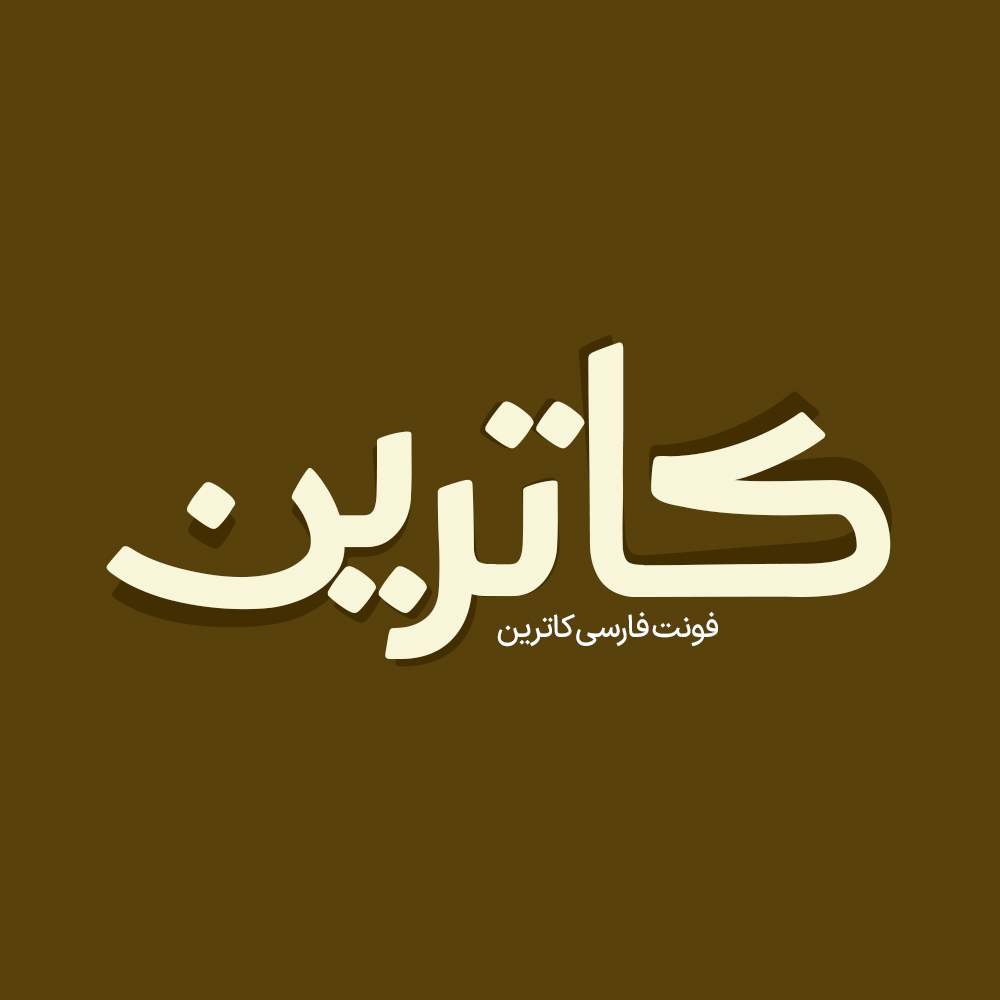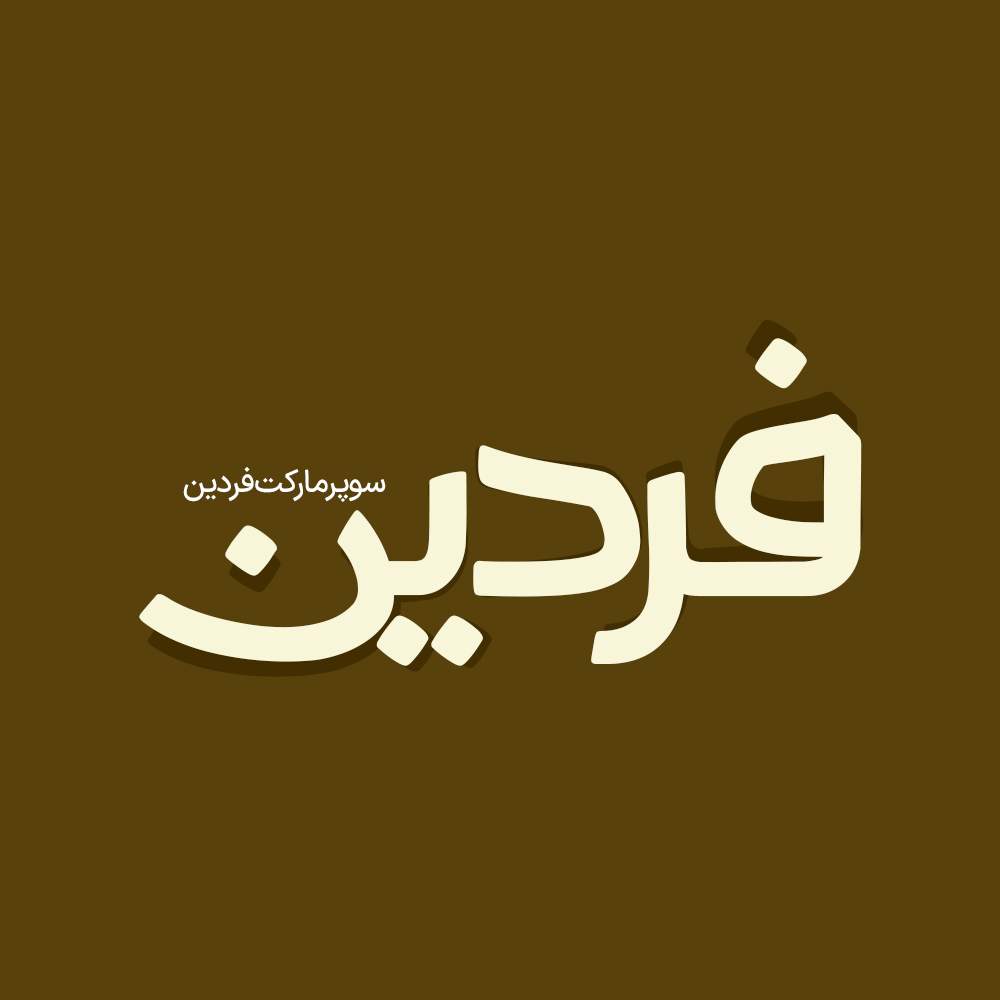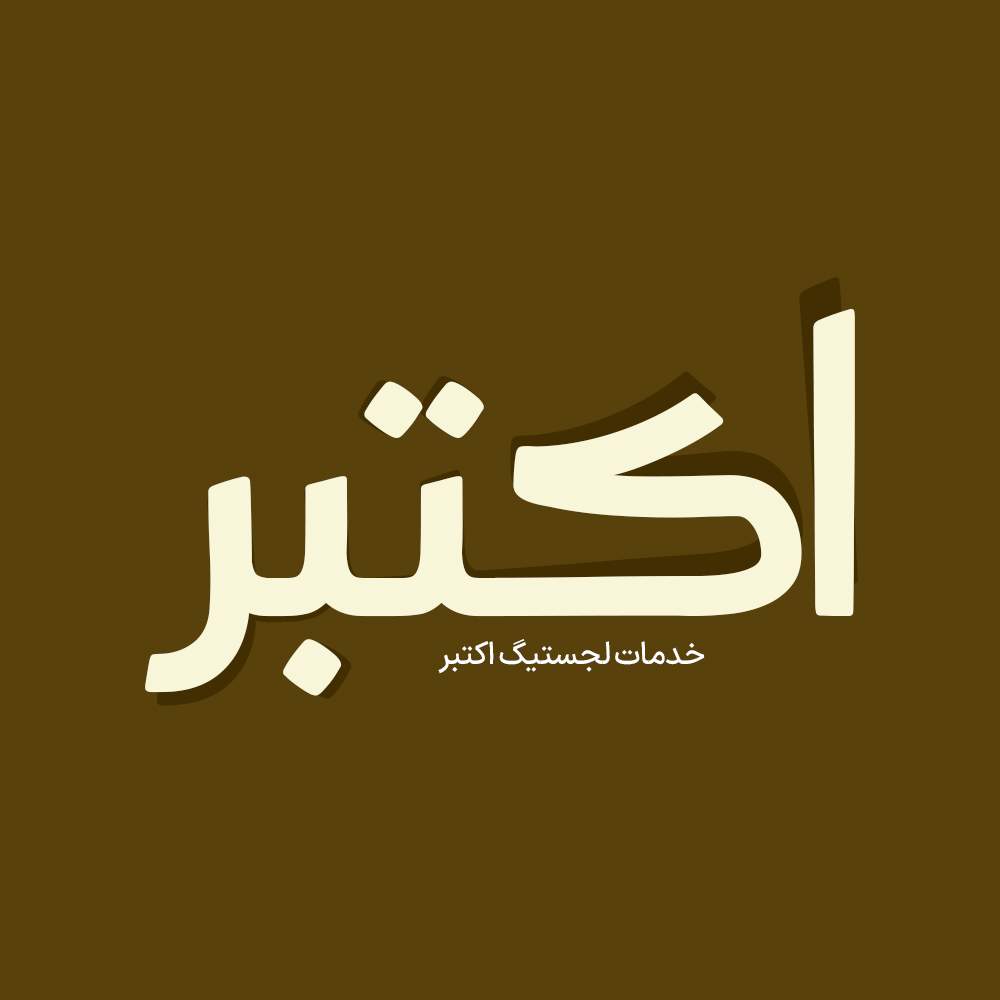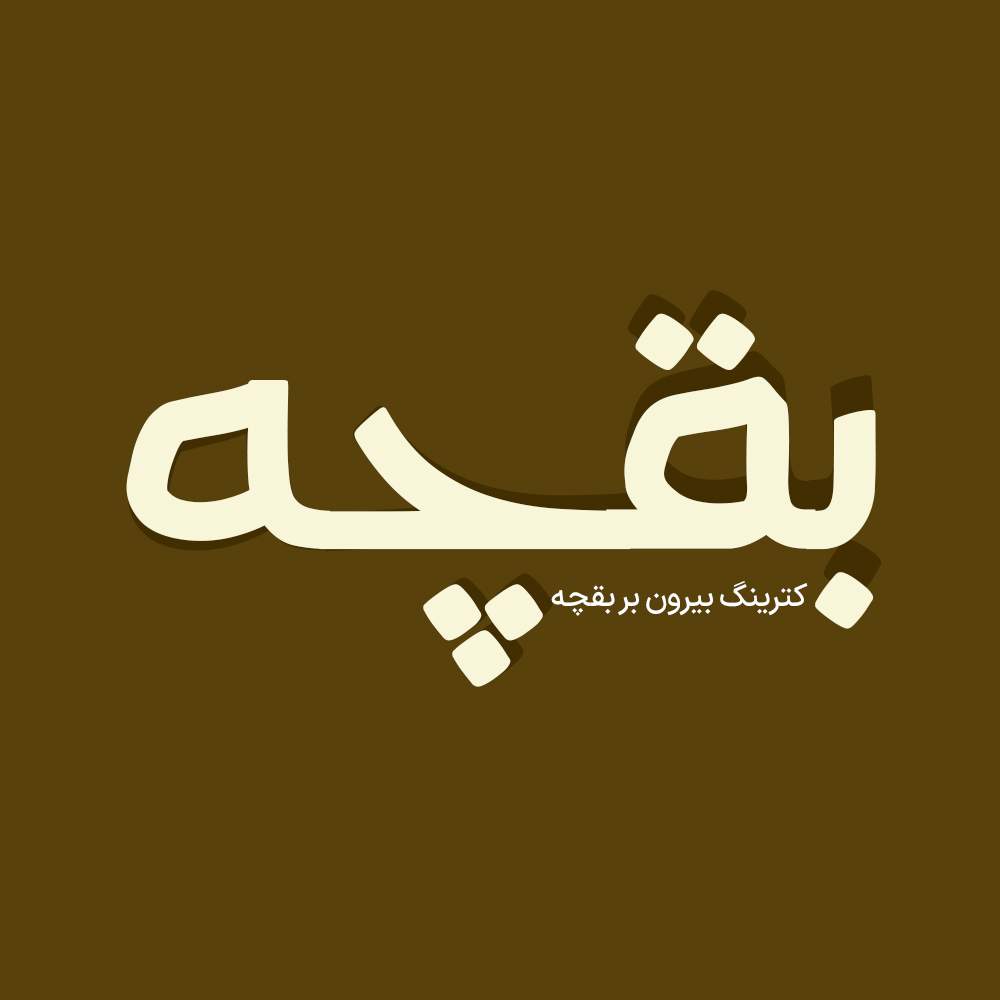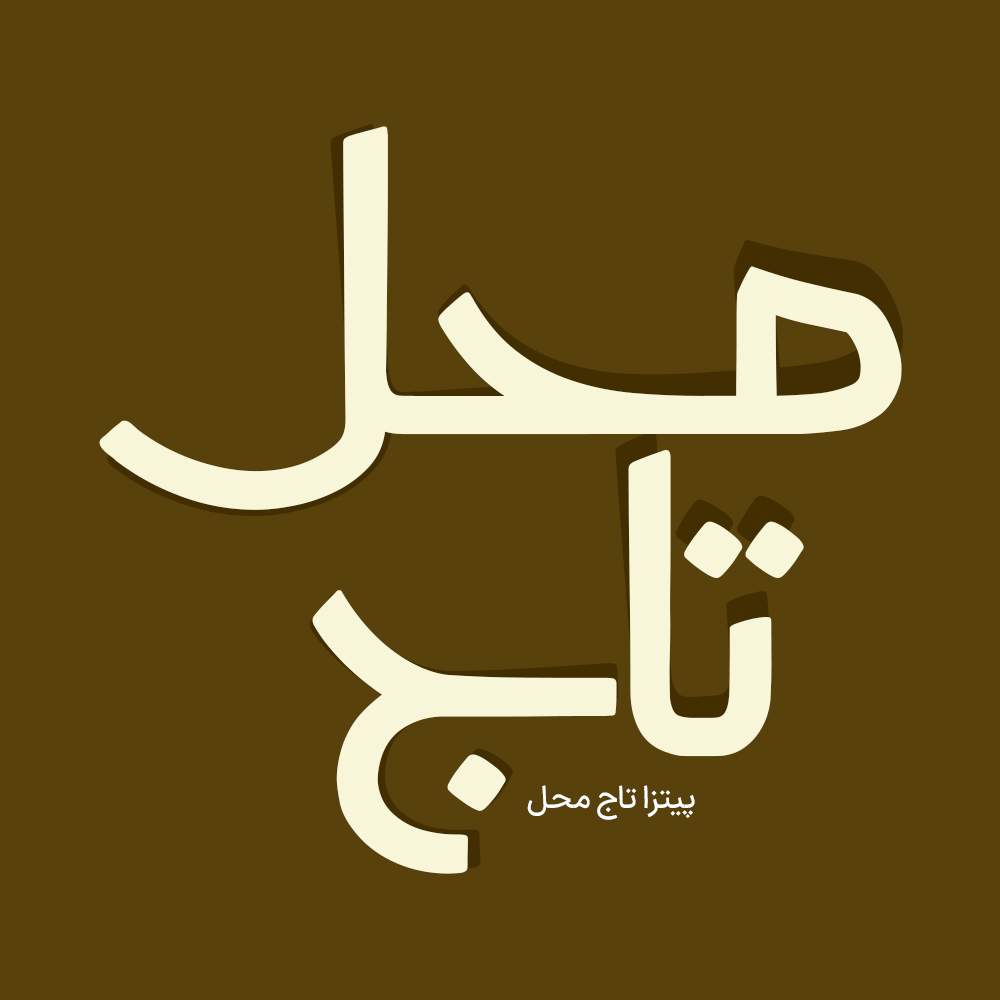
فونت فارسی کاترین Katrin Font
فونت فارسی کاترین یک فونت فارسی بر مبنای حروف هندسی و خاص می باشد که به طراحان گرافیک امکان خلق طرح های زیبا و حرفه ای…
فونت فارسی کاترین یک فونت فارسی بر مبنای حروف هندسی و خاص می باشد که به طراحان گرافیک امکان خلق طرح های زیبا و حرفه ای به سادگی یک تایپ میدهد. فونت کاترین برای لوگو، متنهای کوتاه و صفحه نمایش بهینه شده است. در ادامه برای شما نمونه تایپ های این محصول حرفه ای رو آماده کردیم که میتونید مشاهده کنید.
پیشنمایش و نمونه تایپ های فونت کاترین